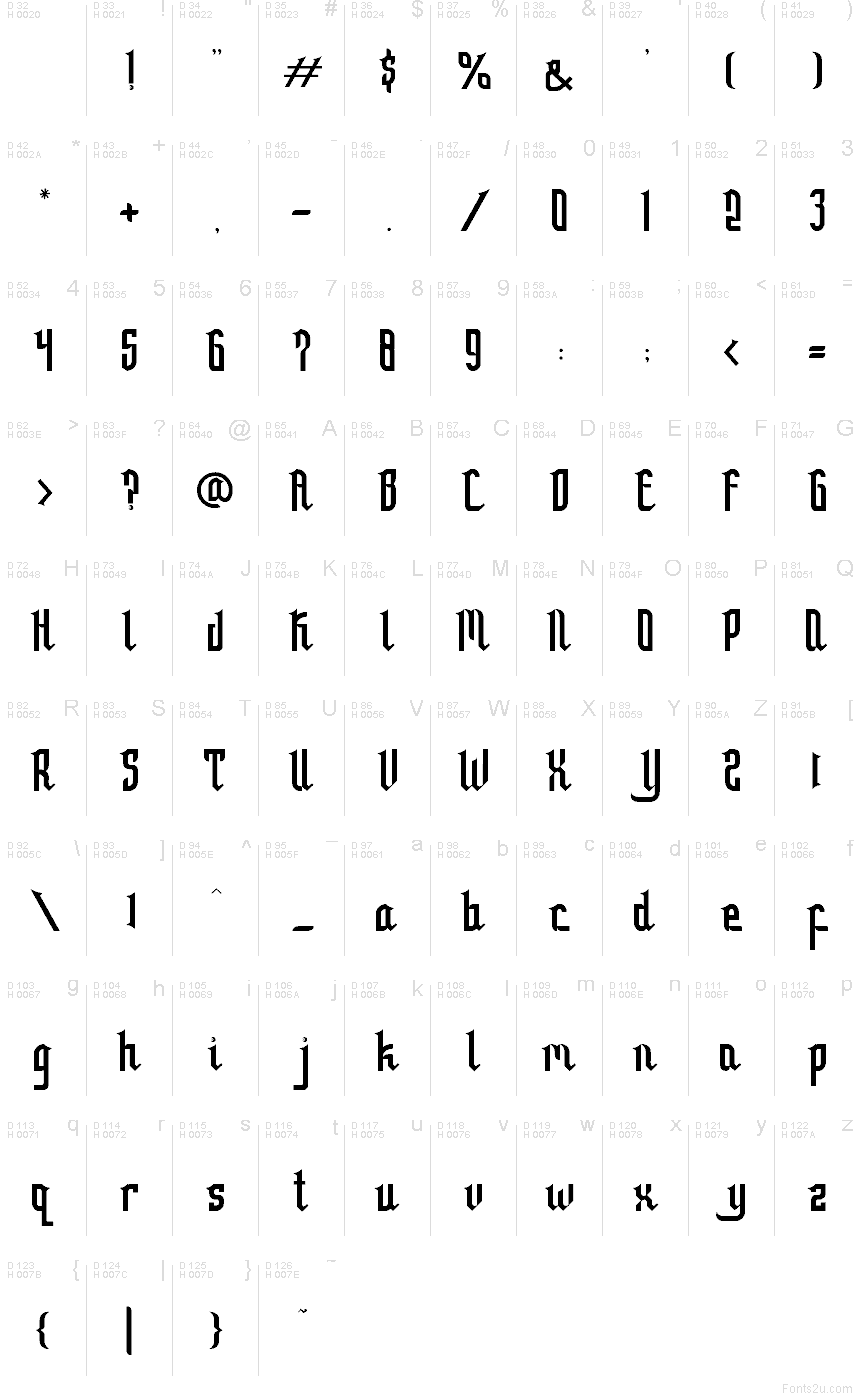
Hikaya Mirage von Putracetol Studio ist eine kostenlose Display-Schriftart mit arabisch inspiriertem Design. Ihre hohen vertikalen Striche und spitzen Bögen erzeugen eine schmale, feierliche Silhouette. Die Schrift verbindet eine fast blackletter-artige Strichstärke mit hakenförmigen Ausläufen und scharfen Einschnitten, was ihr eine kalligrafische Präsenz verleiht, die eher architektonisch als ornamenthaft wirkt.
Diese Formsprache eignet sich hervorragend für Buchcover, Plakate für Ramadan-Veranstaltungen, Restaurant-Branding, Parfümverpackungen sowie Titelkarten, bei denen eine starke kulturelle Note gefragt ist. Sie kommt besonders bei kurzen Schlagzeilen und logoartigen Schriftzügen zur Geltung, da die langen vertikalen Linien und geschwungenen Endungen kurzem Text eine formelle, emblemartige Anmutung verleihen, ohne dass zusätzliche Dekoration erforderlich ist.